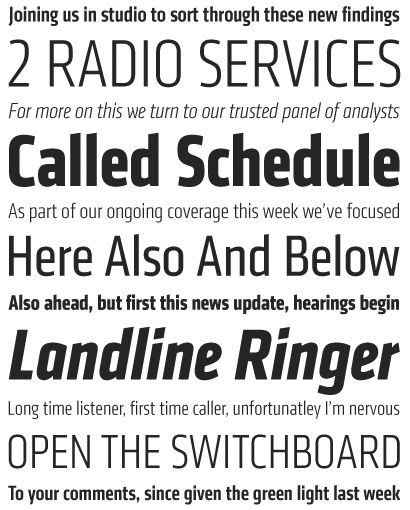
Klavika Condensed (Process Type Foundry)
Klavika Condensed began its life in 2006 when global branding firm FutureBrand
commissioned us to create a custom width of our existing Klavika for the re-brand of
Chevrolet. Although Klavika is already relatively narrow, the new width needed to
accommodate an industry that transmits large amounts of complex information
in tight spaces and relishes the big, bold headline. After two years of exclusive use
by Chevrolet, the retail release of Klavika Condensed is finally available.
Bei der Schmalfetten ist mir ganz spontan die Interstate eingefallen … Naja, ist jetzt nur der allererste Eindruck.
Ich mag die Condensed auch - nur am Paragraphen-Zeichen
der Klavika sollte Herr Olsen endlich etwas ändern!
…nur am Paragraphen-Zeichen der Klavika sollte Herr Olsen endlich etwas ändern!
Unbedingt, unbedingt. Das sieht nach heftigem Ich-will-ganz-was-Besonderes-sein aus. Schade drum.
Ich kann diese seltsame Gestaltung des Paragraphen-Zeichens nachvollziehen.
Es gibt vielleicht Menschen unter uns, die mit Juristerei nichts zu tun haben wollen, und ihre Schrift auf diese Art und Weise „unschädlich“ machen. :huhu:
:peng: Bis man wegen „Plagiaterie“ zum Anwalt muß … Vielleicht doch keine so gute Idee.
In Amerika wird das Zeichen scheinbar kaum verwendet und
deshalb wagt man sich wohl an so »ausgefallene« Varianten.
Das ß ist auch oft ein Kandidat für solche Experimente ...
Bei der Schmalfetten ist mir ganz spontan die Interstate eingefallen … Naja, ist jetzt nur der allererste Eindruck.
genau die ist mir auch eingefallen.
"Wie schön wäre es, wenn ich nicht täglich Interstate vor mir hätte, sondern Klavika."
Klar ist sie anders, aber viel-schöner-anders.
Es gibt vielleicht Menschen unter uns, die mit Juristerei nichts zu tun haben wollen, und ihre Schrift auf diese Art und Weise „unschädlich“ machen.
Interessanter Ansatz, in der Tat. So habe ich das auch noch nie gesehen. Hat was.
Aber, andererseits, wenn man schon Processtypefoundry heißt, sollte man sich doch der Juristerey nicht verwehren … :hammer:
Das ist eine kaputte Büroklammer :-). Wer hat schon sowas im Zeichensatz?
Ansonsten gefällt mir die echt auch sehr gut, obwohl ich sonst nicht unbedingt voreingenommen bin so schmalen Schriften gegenüber. Aber die Klavika macht sich wirklich gut, so schmal. Könnte mir auch vorstellen, dass die am Bildschirm (für so Website-Menu-Zeugs) ein guter Kandidat sein könnte – sie ist bestimmt klein noch gut lesbar.